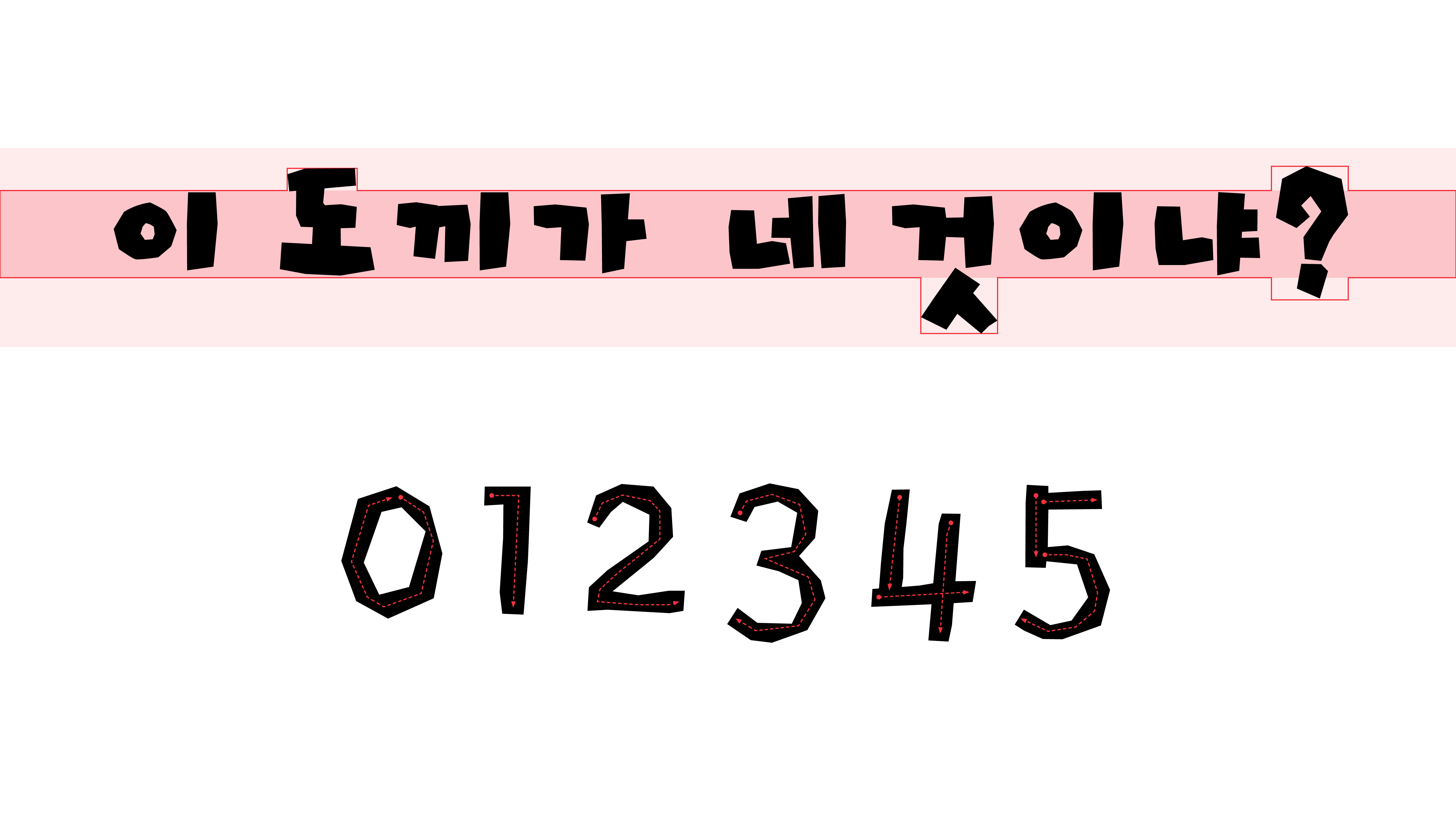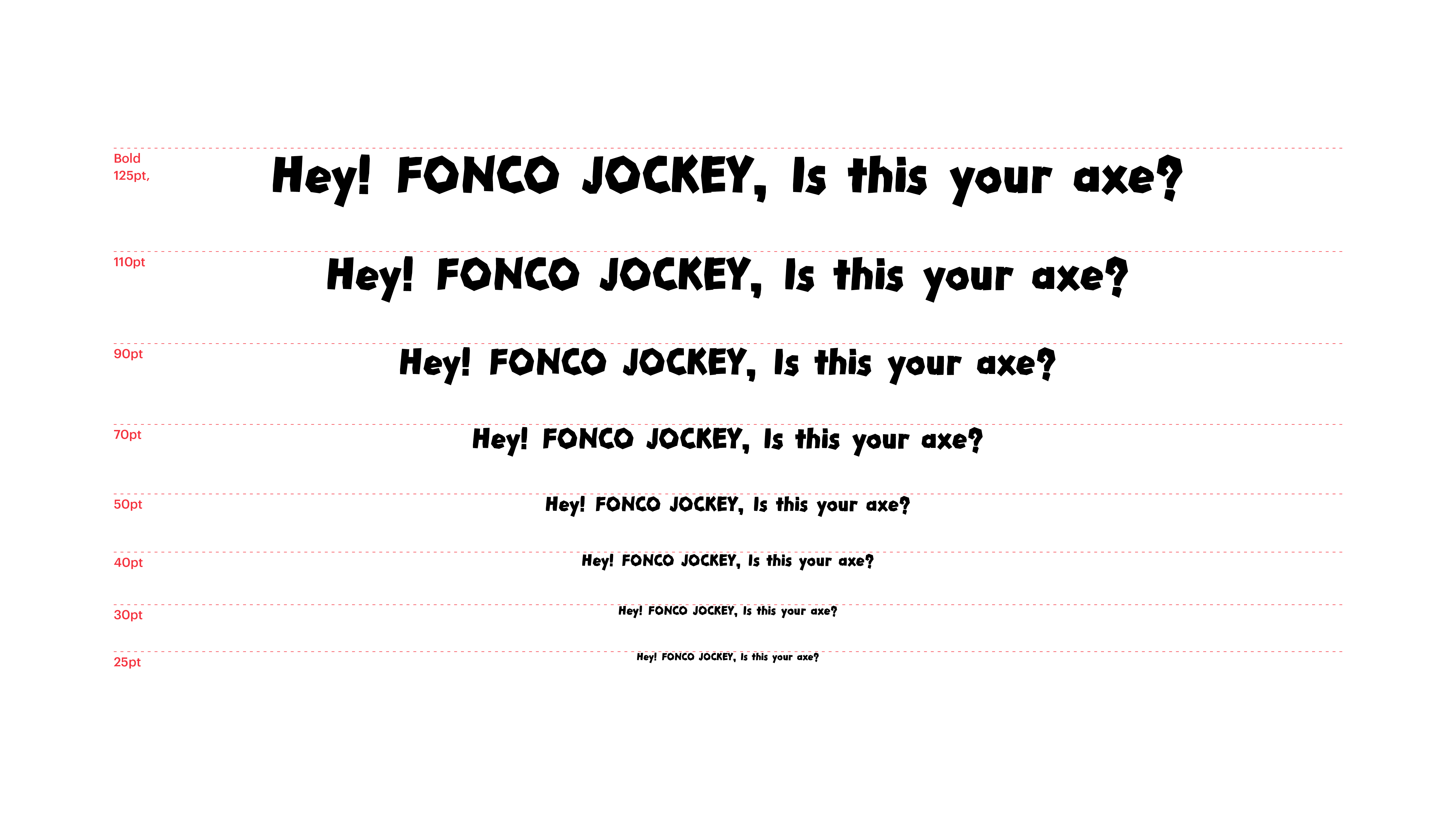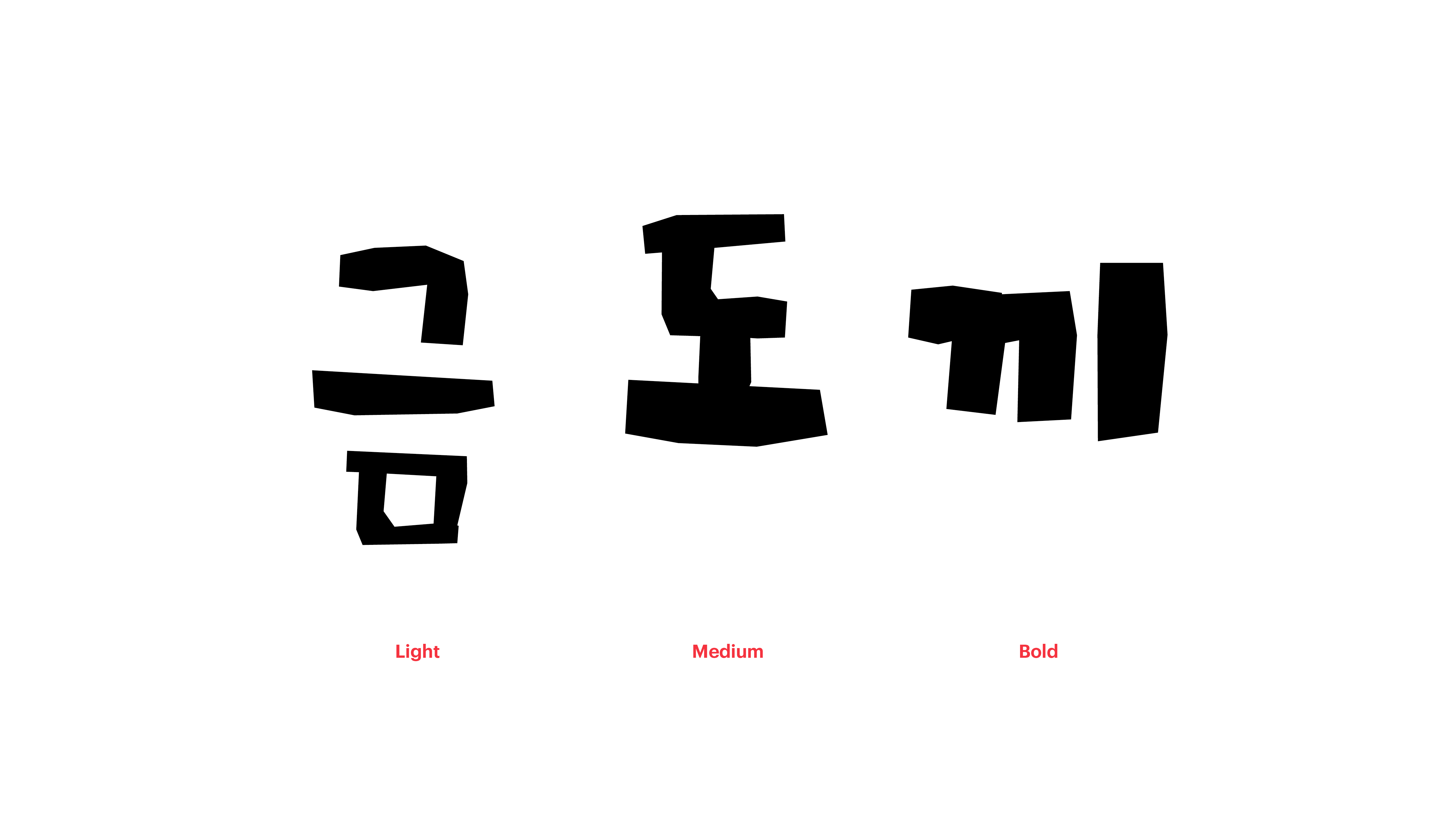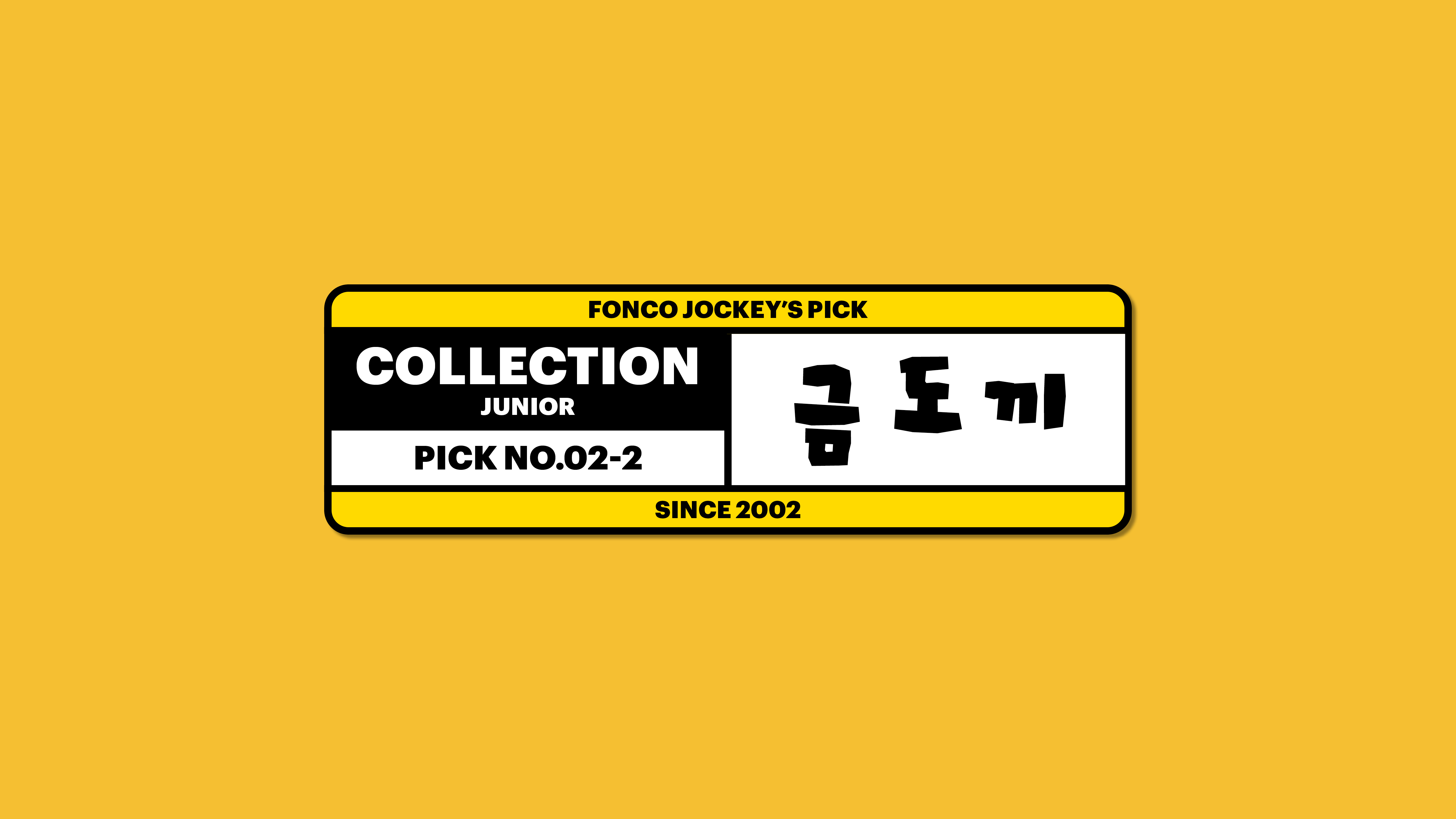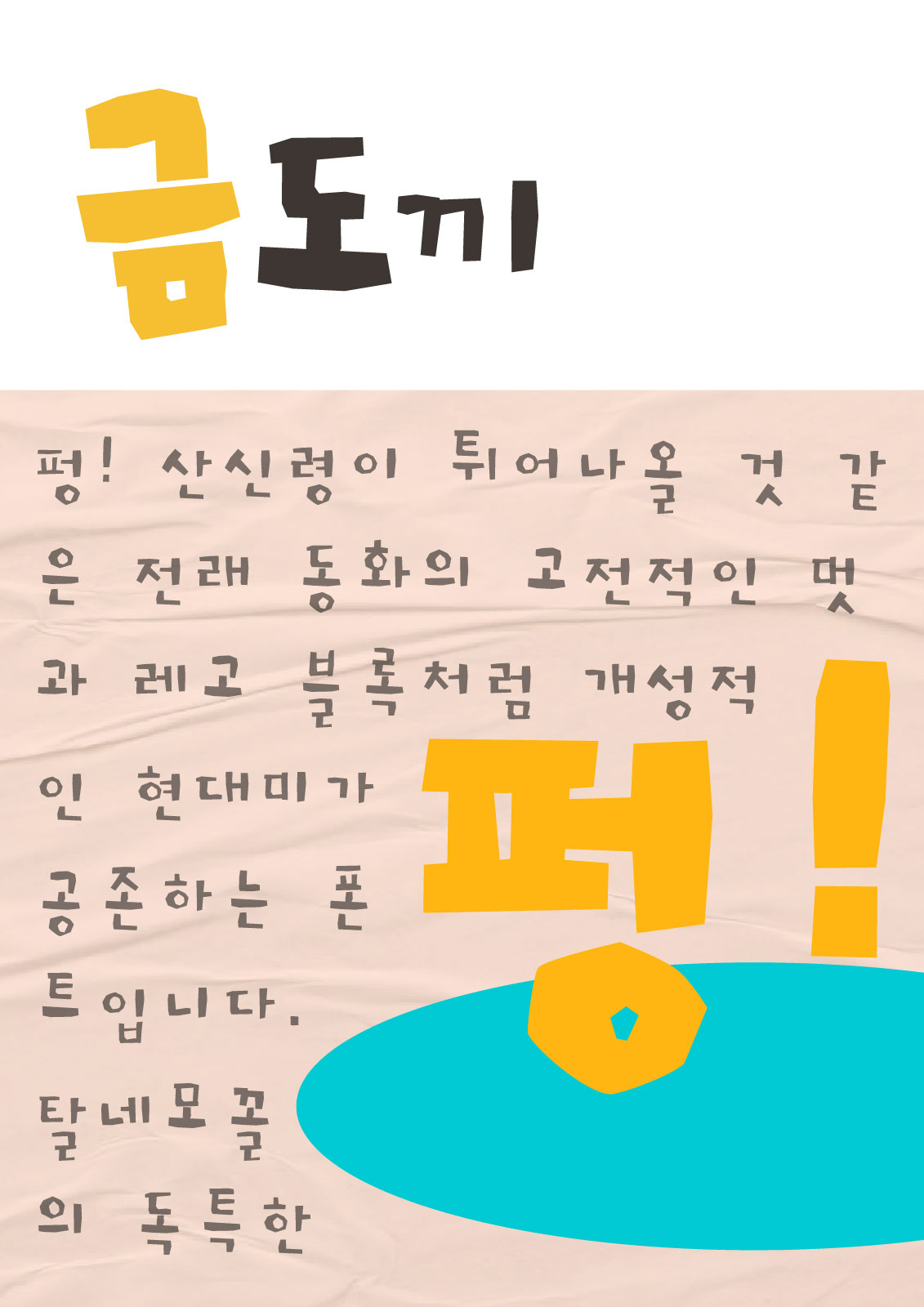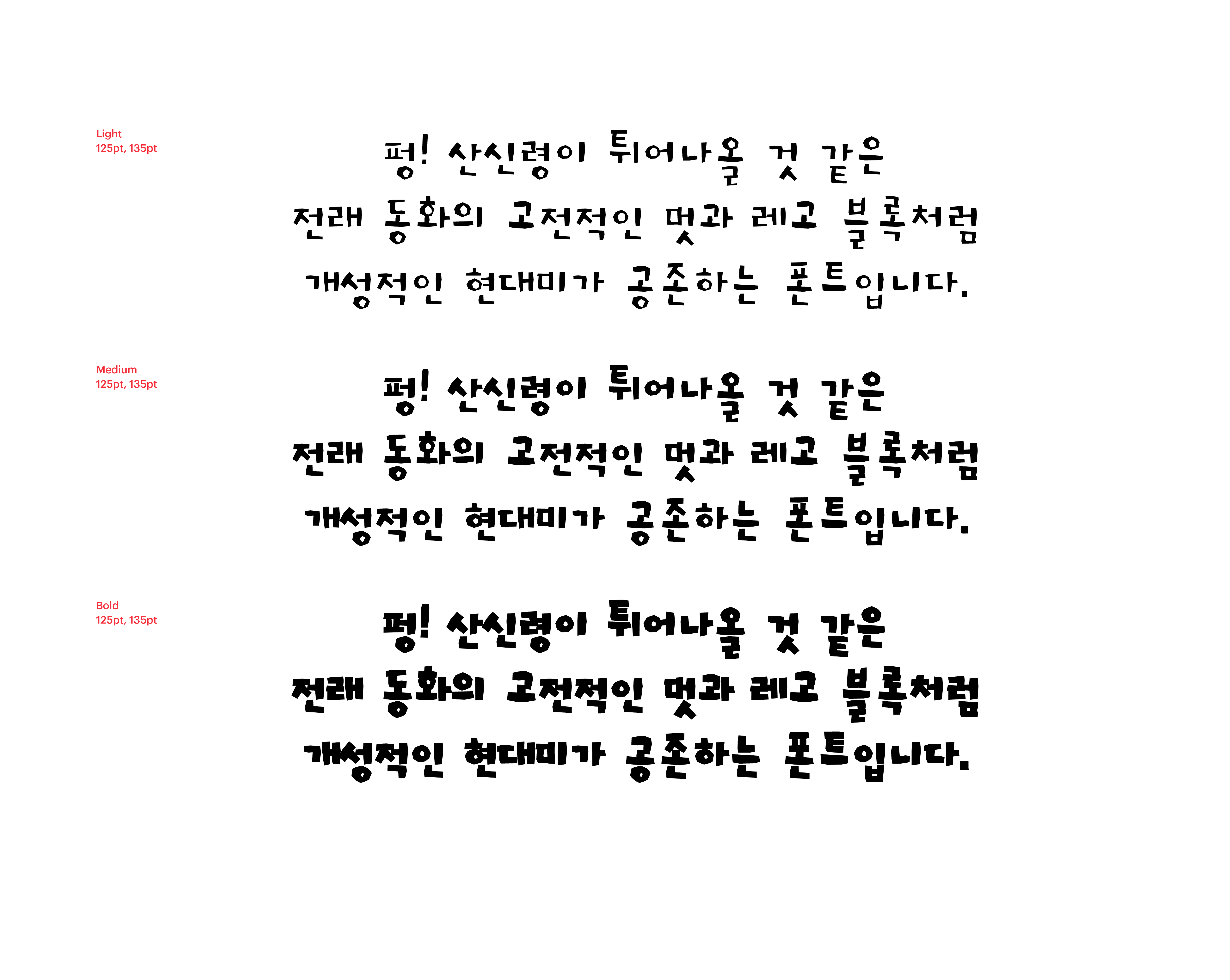
Yoon 금도끼
펑! 산신령이 튀어나올 것 같은 전래 동화의 고전적인 멋과 레고 블록처럼 개성적인 현대미가 공존하는 폰트입니다. 탈네모꼴의 독특한 구조가 유니크한 인상을 자아내지요. 이토록 다양한 매력 덕분에 호랑이 담배 피우던 시절부터 호랑이 전자담배 피우는 오늘날까지. 언제, 어디서나 제약 없이 사용할 수 있답니다.